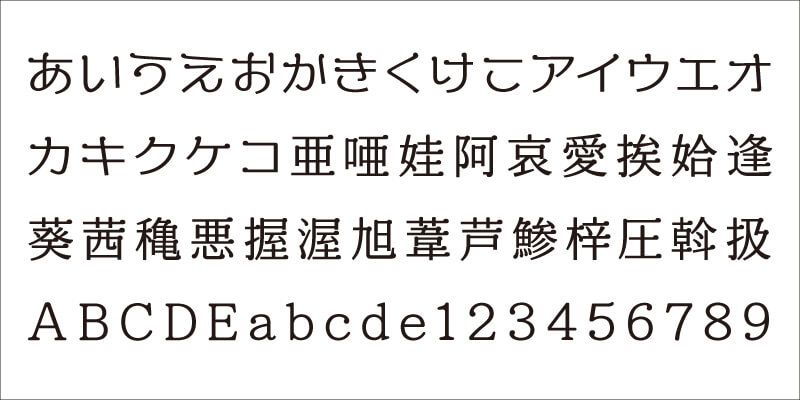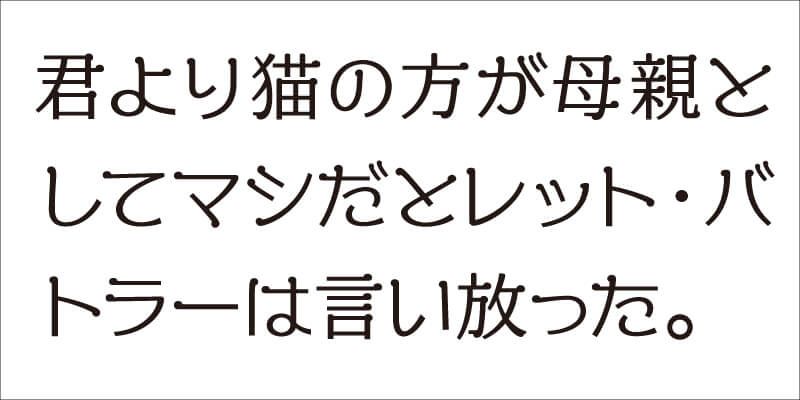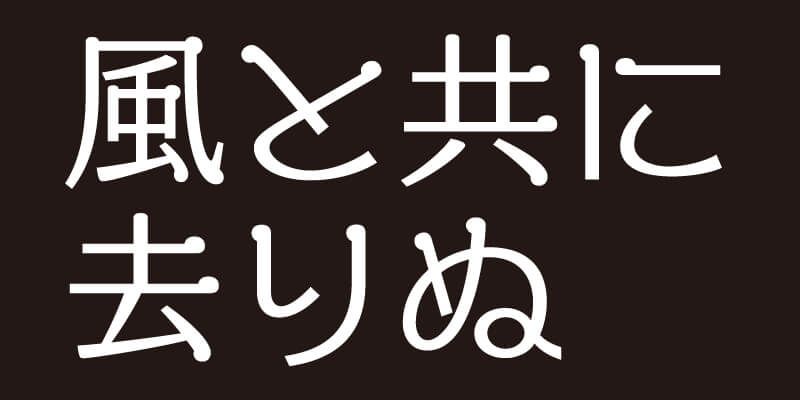
이 서체는 “당신에게 말하는 문자 양식”이라는 개념을 기반으로 했습니다. 일본의 고딕 양식(산세리프) 스타일과 Mincho 스타일의 매력이 있습니다. 독특한 둥근 터미널 모양을 가진 무거운 수평 획을 주목할 만합니다. VDL-ADMin의 시각적 힘과 선명도는 보통 전통적인 Mincho 스타일의 서체에서 볼 수 없지만 여기에선 손으로 쓰여진 것처럼 차분한 모양과 잘 공존합니다.